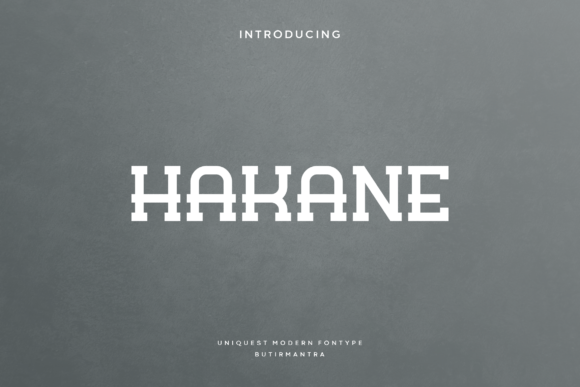
Journey through时光隧é�“,邂逅Hakaneå—体的å¤�å�¤é…åŠ›ï¼Œè®©ä½ çš„è®¾è®¡ä½œå“�æ•£å�‘出浓浓的年代韵味。这款迷人的衬线显示å—体,承载ç�€å²�月的å�°è®°ï¼Œä»¿ä½›æ�¥è‡ªé�¥è¿œçš„æ—¶å…‰ï¼Œå°†ä½ 的创作带入ç»�典与怀旧的交å“�曲之ä¸ã€‚
Hakaneå—ä½“ä»¥å…¶ç‹¬ç‰¹çš„æ€€æ—§é£Žæ ¼ï¼Œåœ¨å±�å¹•ä¸Šç† ç† ç”Ÿè¾‰ã€‚å®ƒçš„æ¯�一个笔触都仿佛诉说ç�€ä¸€æ®µæ‚ 长的故事,仿佛有生命的精ç�µåœ¨çº¸ä¸Šèˆžè¹ˆã€‚æ— è®ºä½ æ˜¯è®¾è®¡æµ·æŠ¥ã€�网页ã€�还是其他视觉作å“�,Hakaneå—体都能æˆ�ä¸ºä½ ä¸�å�¯æˆ–缺的创作利器。
这套å—体包å�«ä¸€ç³»åˆ—精心设计的å—符,从大å°�写嗿¯�到数å—和符å�·ï¼Œåº”有尽有。æ¯�个å—符都ç»�过精心雕ç�¢ï¼Œç»†èŠ‚ä¹‹å¤„å°½æ˜¾åŒ å¿ƒã€‚æ— è®ºæ˜¯ä¼˜é›…çš„æ›²çº¿ä¸Šæ‰¬ï¼Œè¿˜æ˜¯åˆšåŠ²æœ‰åŠ›çš„ç¬”é”‹è½¬æŠ˜ï¼ŒHakaneå—ä½“éƒ½èƒ½å®Œç¾Žå‘ˆçŽ°ï¼Œè®©ä½ çš„ä½œå“�充满艺术气æ�¯ã€‚